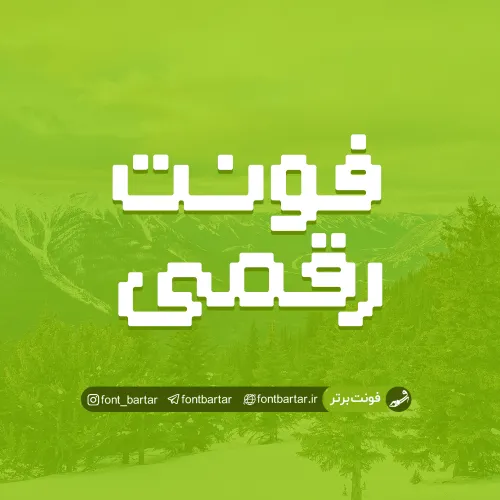
فونت فارسی رقمی
فونت فارسی بسیار زیبا و جدید به نام رقمی که ترجمه شده از عربی به معنی دیجیتا است این فونت با ظاهری پیکسلی مناسب برای استفاده در پروژه های صحنه نمایش و همچنین ال ای دی می باشد.
فونت رقمی مورد استفاده برای:
- طراحان وب سایت و گرافیست های خلاق می توانند از این مجموعه زیبا فونت در طراحی پروژه های تبلیغاتی و تجاری خود کمک بگیرند.